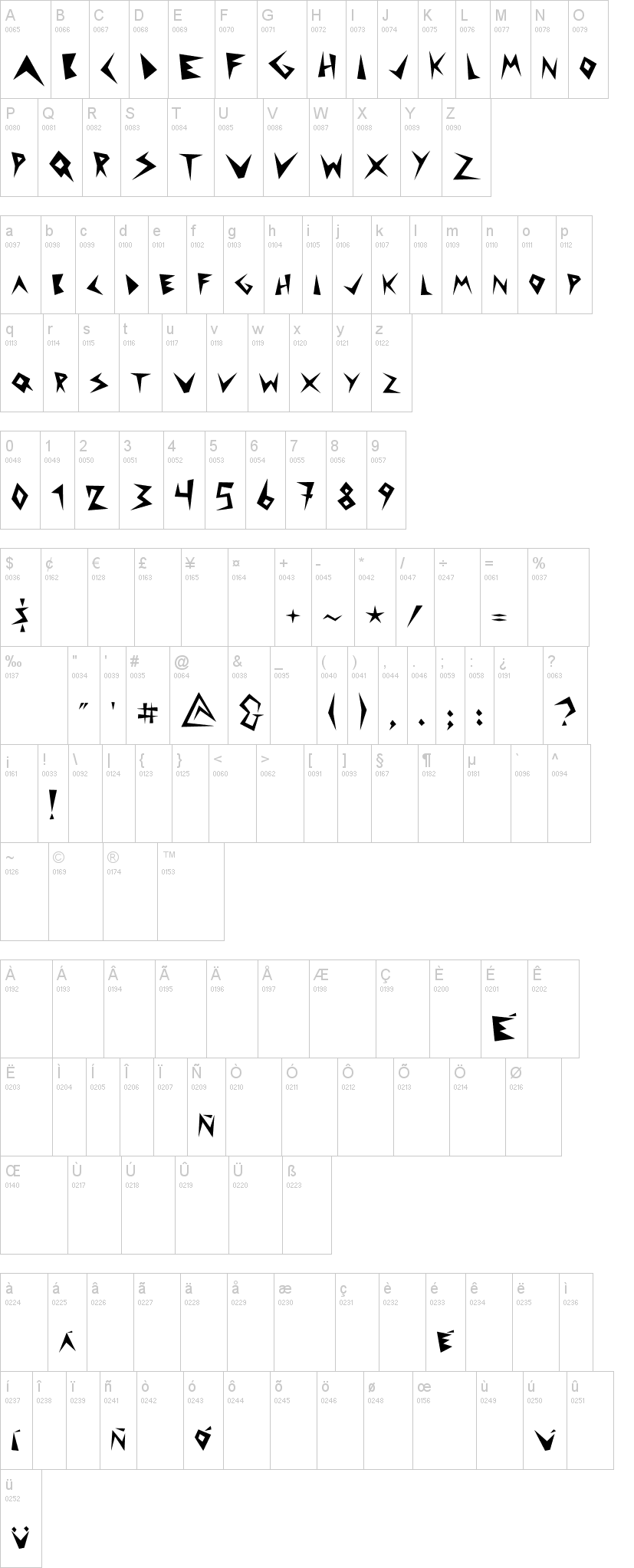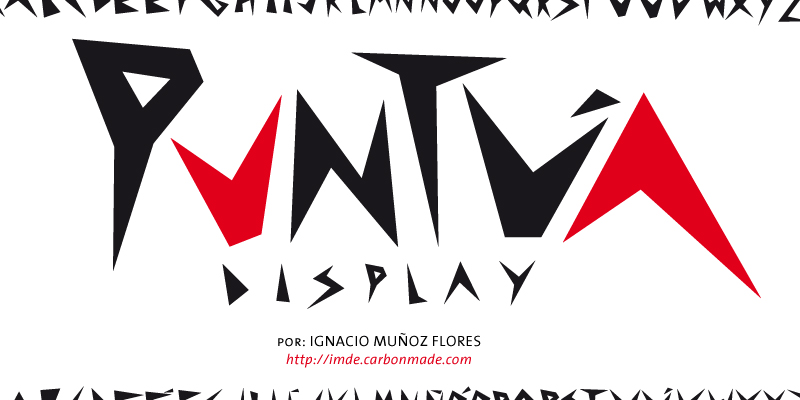
Шрифт Puntúa Display
PUNTÚA DISPLAY.
La tipografía para enterrar en todas partes, matar y dejar ciegos a lectores odiados. made in Chile, realizada como proyecto personal para un afiche.